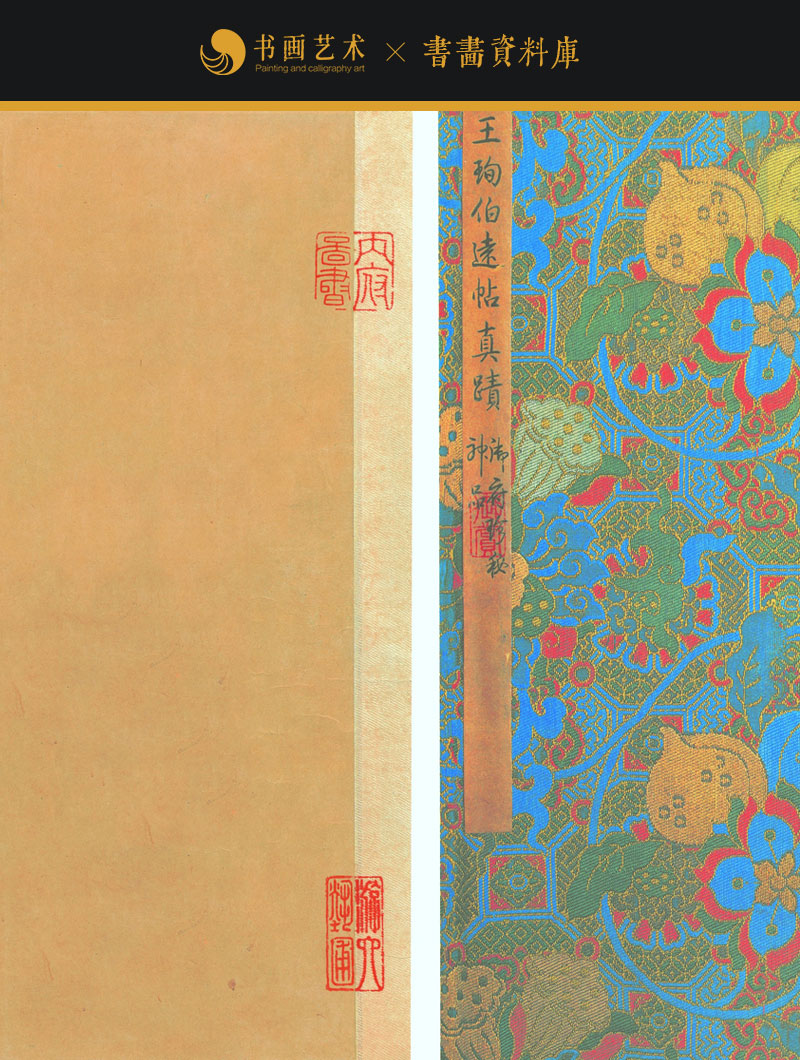
孤月满楼 书画资料库 2020-10-22 《三希帖-伯远帖》行书.晋.王珣书.超高清下载JPG+PDF 《伯远帖》是东晋书法家王珣创作的行书书法作品。现收藏于北京故宫博物院。《伯远帖》是作者给亲友伯远书写的一通信札,其行笔自然流畅,俊丽秀雅,为行书早期的典范之作。全篇随其本字之形,顺其自然之态,而又通篇和悦,自然一体,有如天成。 4 您已点过赞 书法资料 精选推荐 版权说明相关作品:版权为原创作者所有,如您不允许转,我们将及时处理! 相关资料:网络收集资源,版权(C)归原作者所有,仅供交流学习!